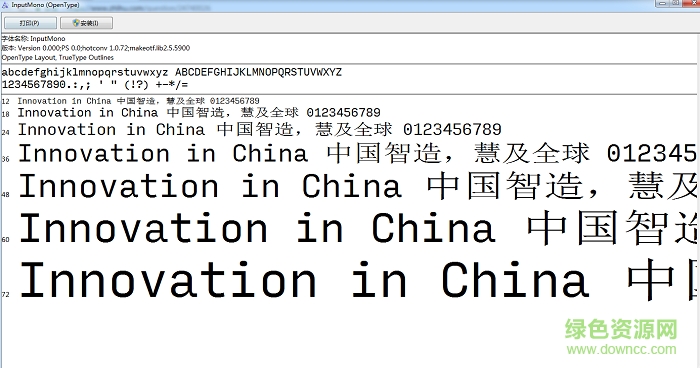
font ligatures是一款易于辨識(shí)的編程字體,該字體粗細(xì)一致,清晰度高,顯示大量代碼時(shí)也容易看清,適合從事相關(guān)編程工作的朋友使用,有需要者快來綠色資源網(wǎng)下載吧!
一款擁有高辨識(shí)度的等寬字體,支持?jǐn)U展字符集以及相似字符,字形看起來非常整潔!